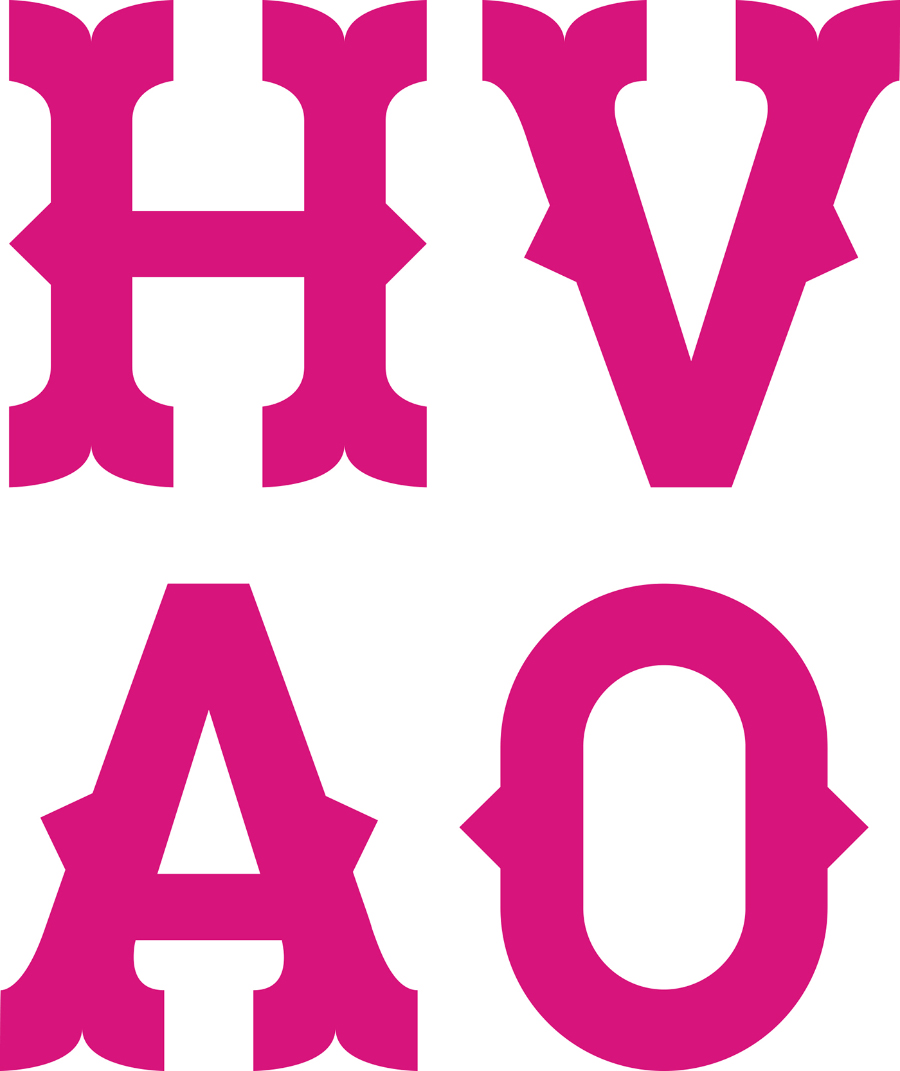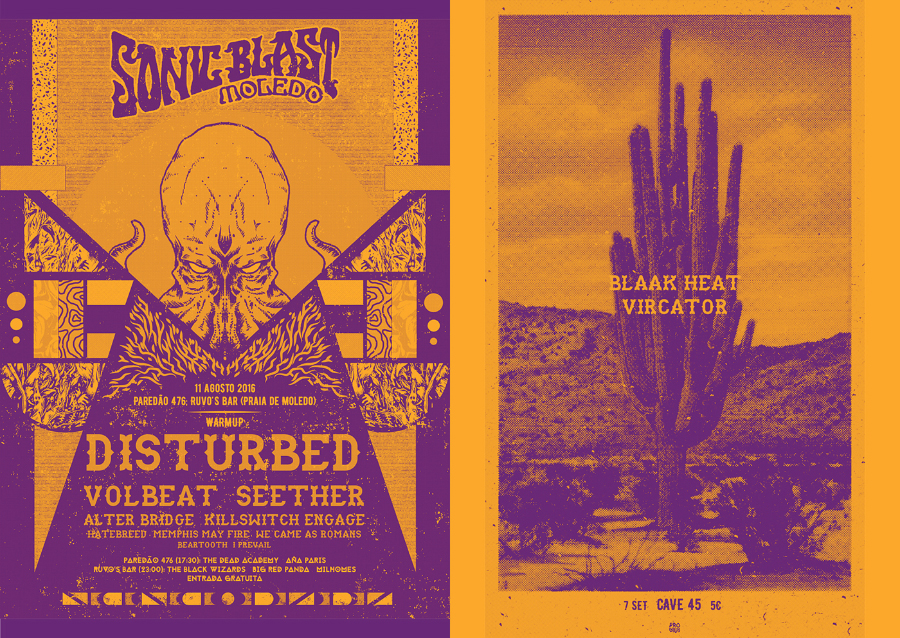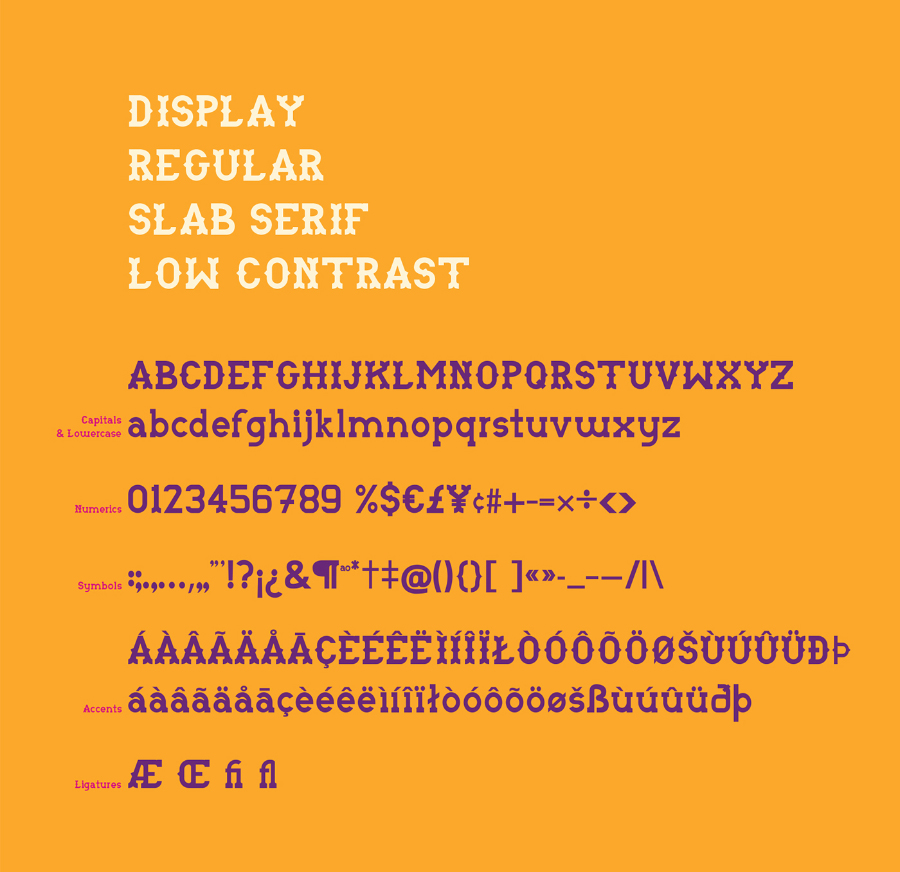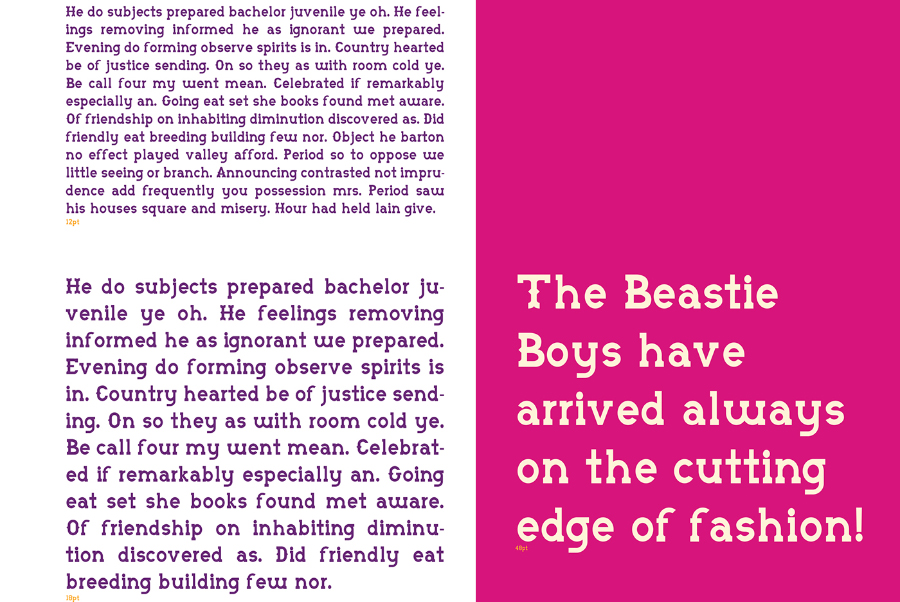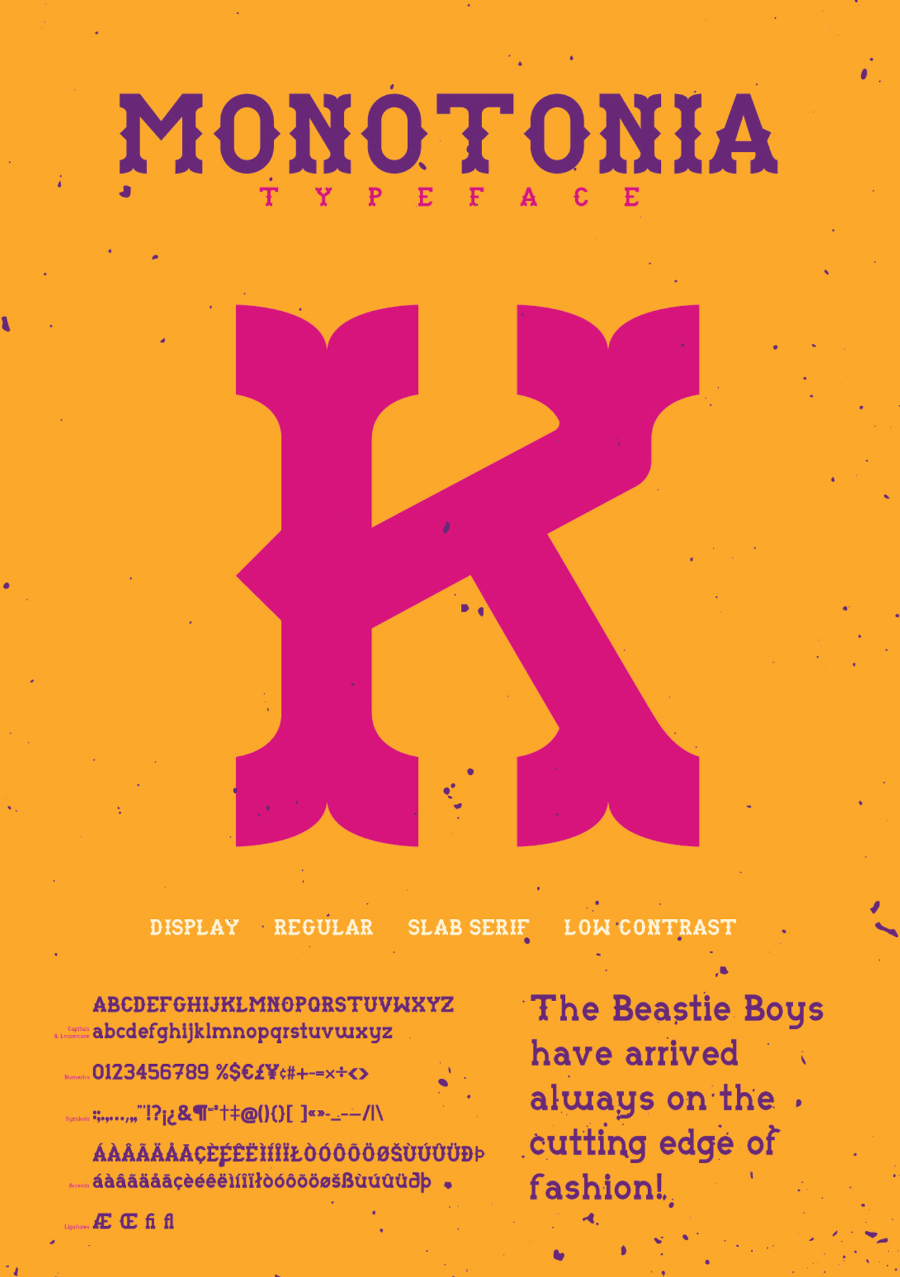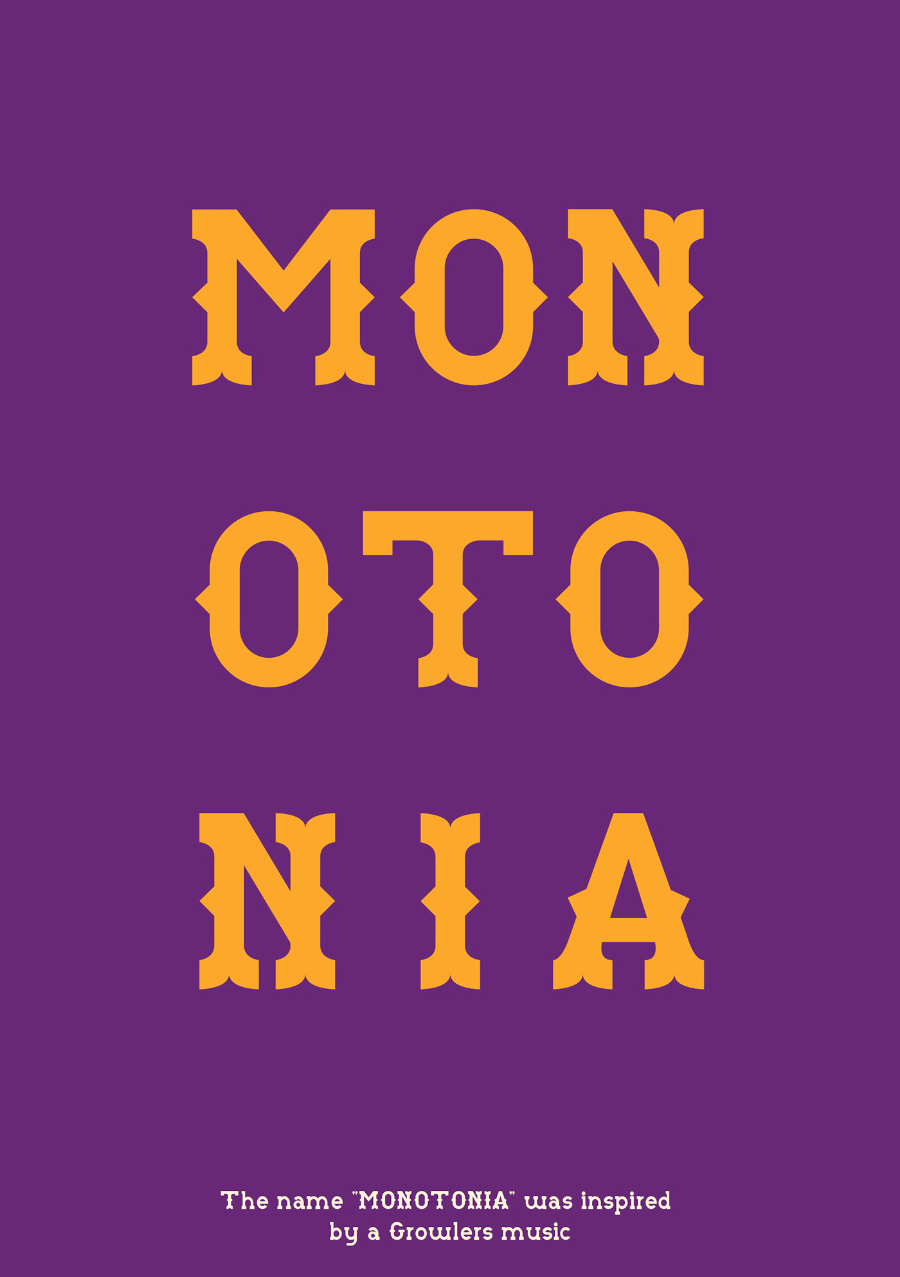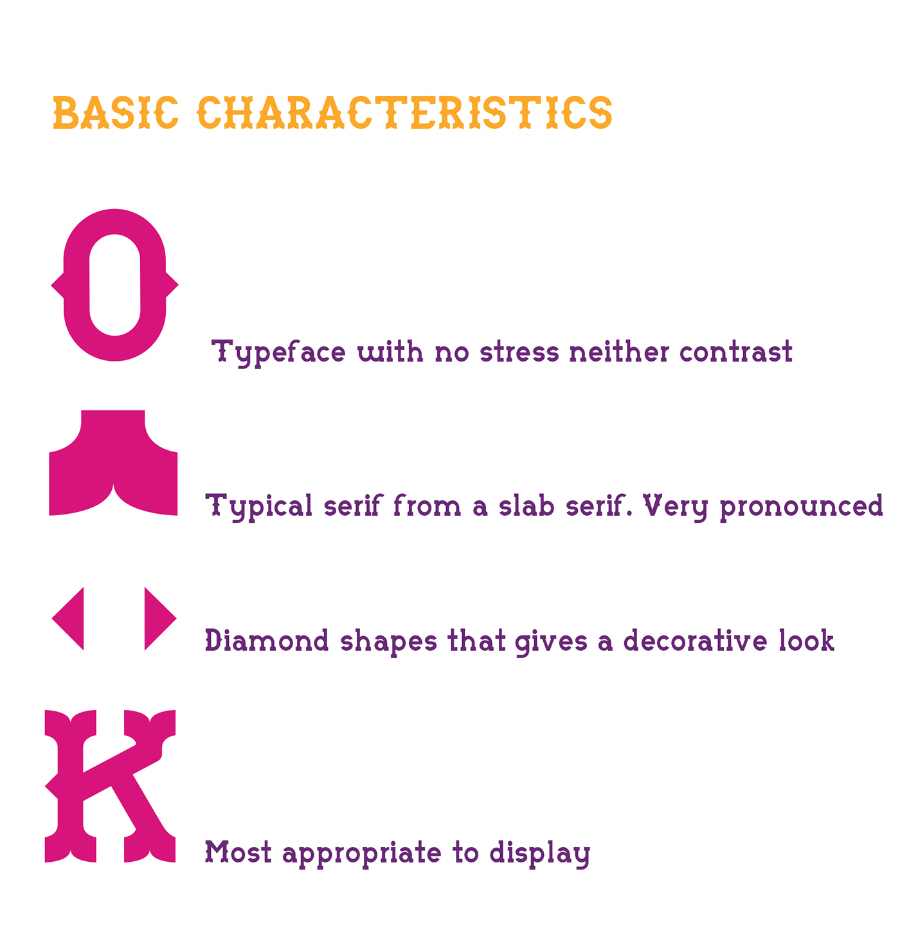
Monotonia显示自由字体
Monotonia显示免费字体今天为您服务! Eduardo da Floresta最新鲜的免费赠品。正如我们在预览中看到的那样,这种字体有能力为您的设计增添有吸引力的感觉。 Monotonia是伟大的海报,标题,标志等等。此外,这是免费的个人和商业用途。所以,现在下载,并有一些乐趣!